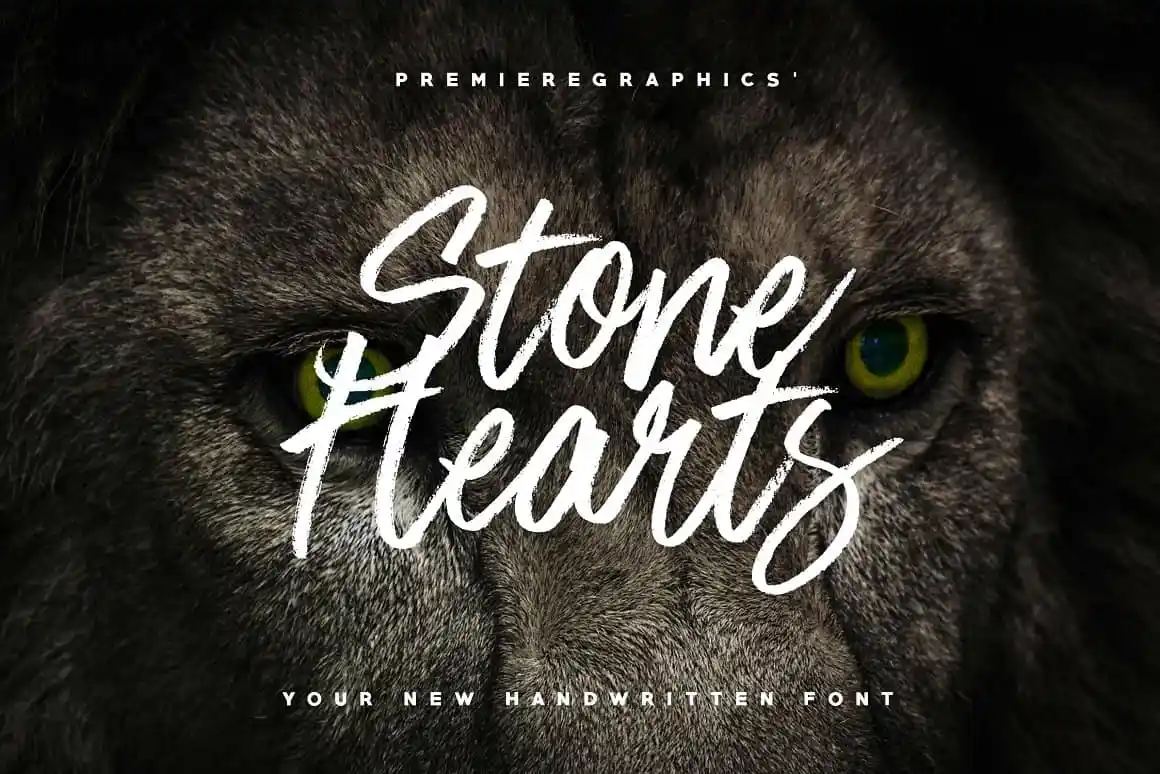
Stone Hearts Brush Font – Download Grátis
A Stone Hearts Brush Font é uma elegante escolha para designers que valorizam a autenticidade nos projetos. Essa fonte script foi criada e compartilhada pelo designer Premiere Graphics, oferecendo um look cuidadosamente realista de marca, logo e embalagem. Ela não se limita aos padrões tradicionais de uma fonte para o Dia dos Namorados; em vez disso, é uma mistura suave e agressiva que captura uma verdadeira personalidade única. A Stone Hearts Brush Font foi criada usando um marcador seco, garantindo uma aparência matizada perfeita. Seu design meticulosamente cuidado cria um ar de autenticidade, tornando-a ideal para a criação de designs gráficos, anúncios e identidades visuais. Suas linhas fortes e delicadas permitem que ela se destaque tanto em logotipos quanto em mensagens inspiradoras ou letras decorativas. A Stone Hearts Brush Font é perfeita para quem busca uma fonte que transmite confiança, paixão e força. Seja você um designer gráfico ou criador de conteúdo, essa fonte pode trazer a sua ideia à vida com uma personalidade única. Não apenas complementa qualquer projeto que você está trabalhando, mas também torna-o ainda mais especial e memorável.